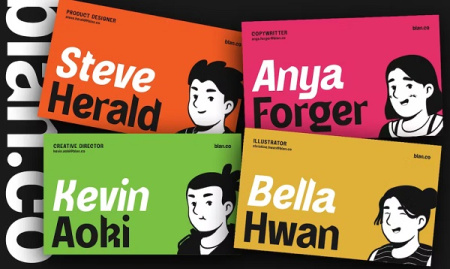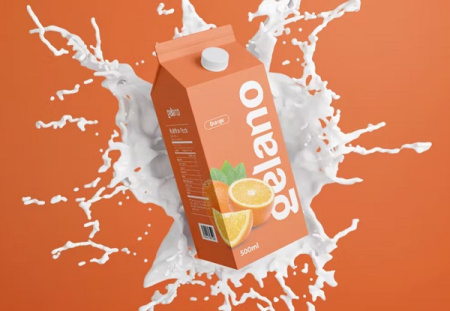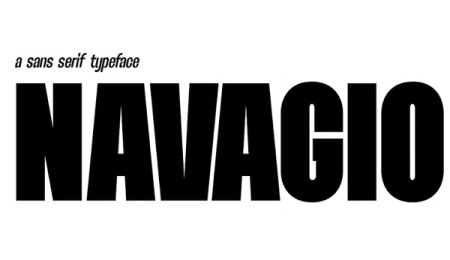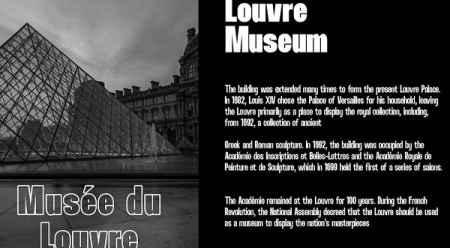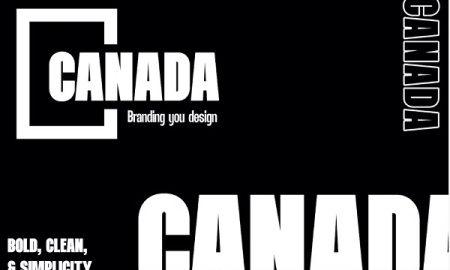
فونت انگلیسی سایت شامل 2 فونت زیبای انگلیسی برای وب سایت است. این تایپ فیس با جذابیت خود، حس جادویی را به پروژه های خلاقانه شما می بخشد. همچنین این مجموعه برای برندسازی ، طراحی عنوان، پروژه ها یا هر چیزی که فکرش را بکنید عالی است! برای مشاهده تصاویر این فونت در ادامه مطلب با سایت gfx همراه باشید.
این فونت انگلیسی زیبا را در ادامه با تهیه اشتراک ویژه از جی اف ایکس دانلود تهیه کنید و برای ایجاد نام تجاری، آرم ها، مجلات، فیلم ها، پوستر، نقل قول ها، عکاسی، دعوت نامه، وبلاگ، تبلیغات، کارت پستال، کتاب، رسانه های اجتماعی، وب سایت، و غیره از آنها استفاده کنید.
✅ نام فونت انگلیسی1: magic ruby ✅ نام فونت انگلیسی2: navagio ✅ پشتیبانی چند زبانه ✅ شامل اعداد و علائم نگارشی ✅ لینک دانلود مستقیم از سرور ایران